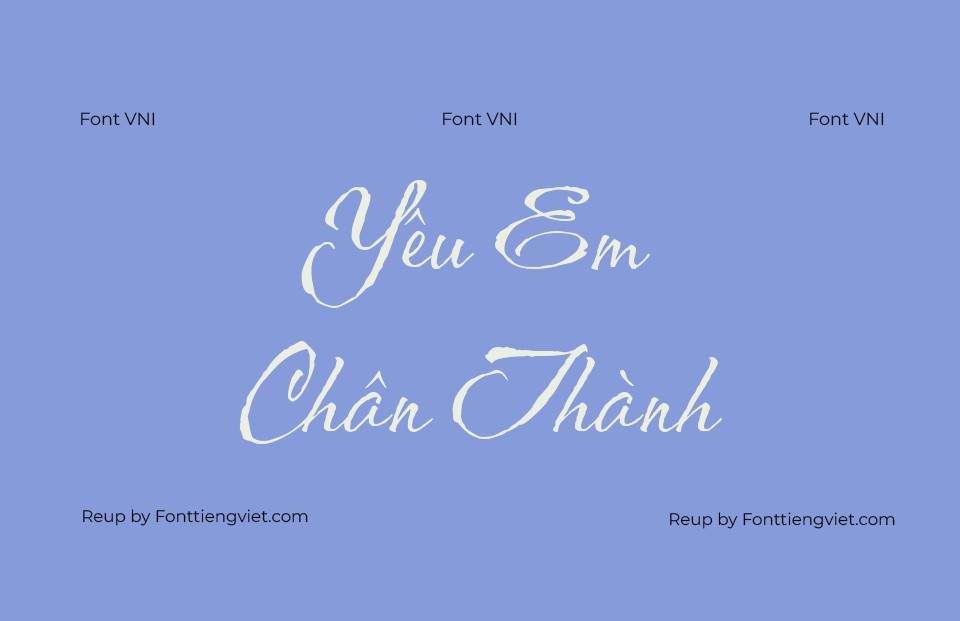
Font Việt hoá VNI 30 ShishoniBrush
Giới thiệu về Font Việt hoá VNI 30 ShishoniBrush
Trong thế giới đồ họa, việc lựa chọn một bộ Font Miễn Phí ấn tượng đóng vai trò quyết định đến linh hồn của tác phẩm. Font Việt hoá VNI 30 ShishoniBrush là một trong những kiểu chữ độc đáo nhất thuộc bảng mã VNI, mô phỏng hoàn hảo những nét vẽ thủ công từ cọ lông truyền thống. Với các đường nét mạnh mẽ, dứt khoát nhưng không kém phần uyển chuyển, bộ font này cực kỳ phù hợp cho những ai muốn truyền tải thông điệp mang đậm tính nghệ thuật hoặc phong cách cổ điển Á Đông.
Đặc điểm nổi bật của Font Việt hoá VNI 30 ShishoniBrush
Phong cách thư pháp ấn tượng
Đặc trưng lớn nhất của Font Việt hoá VNI 30 ShishoniBrush chính là hiệu ứng “vết cọ” khô tự nhiên. Từng ký tự đều có độ đậm nhạt khác biệt, tạo cảm giác như đang được viết trực tiếp trên giấy xuyến chỉ. Điều này giúp các bạn học sinh và giáo viên dễ dàng tạo ra những tấm thiệp chúc mừng, tiêu đề bài giảng hoặc các biểu ngữ sự kiện trường học vô cùng bắt mắt và trang trọng.
Ứng dụng đa dạng trong thiết kế
Không chỉ dừng lại ở các tài liệu học tập, font chữ này còn được sử dụng rộng rãi trong thiết kế bìa sách, poster phim hoặc các sản phẩm quảng cáo đòi hỏi sự phá cách. Nhờ vào quá trình Việt hóa kỹ lưỡng, các dấu thanh tiếng Việt được đặt vị trí chuẩn xác, giúp văn bản trình bày mạch lạc, không bị lỗi hiển thị khi soạn thảo trên các phần mềm như Word, Photoshop hay Illustrator.
Lưu ý khi sử dụng và kết luận